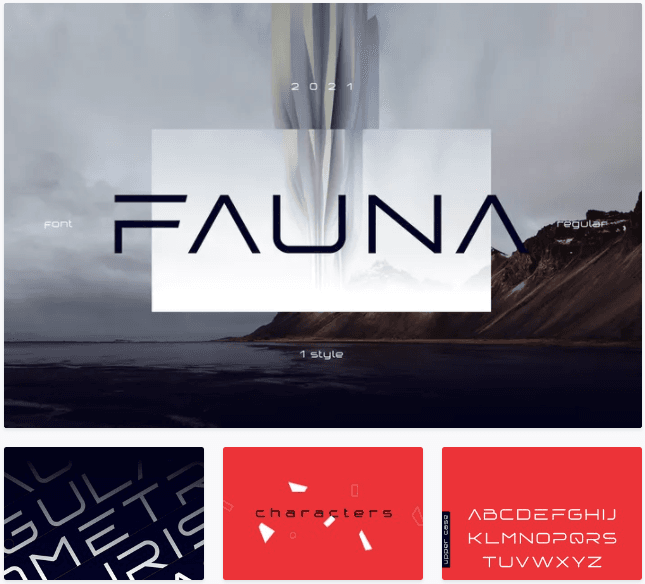
Fauna font
Имя шрифта: Фауна \ Стиль: Обычный \ Год выпуска: 2021
Fauna - это стильный шрифт, вдохновленный Hi-Fi элементами в сочетании с квадратными формами и прямыми линиями. Он также имеет особенности конструктивизма, включая солидность, акцент на геометрические формы и жесткую экономию. Смелые футуристические персонажи делают этот шрифт идеальным вариантом для разработки минималистичного и узнаваемого дизайна, необходимого для любого современного проекта.
Он идеально подходит для создания Логотипы типов, названий, сообщений в социальных сетях, плакатов и объявлений. Благодаря четкому и привлекательному дизайну персонажей, шрифт обязательно привлечет вашу аудиторию.
Она включает в себя все основные символы и символы. Кроме того, Fauna имеет правильный кернинг и поддерживает несколько языков. Прямо сейчас доступен только обычный стиль шрифта.